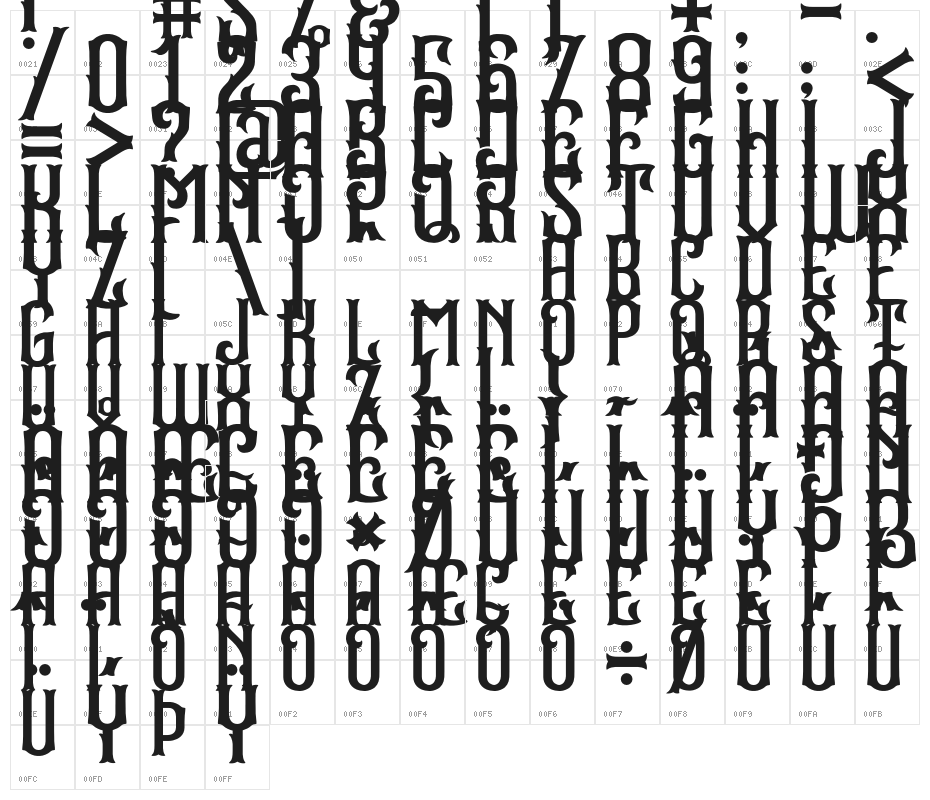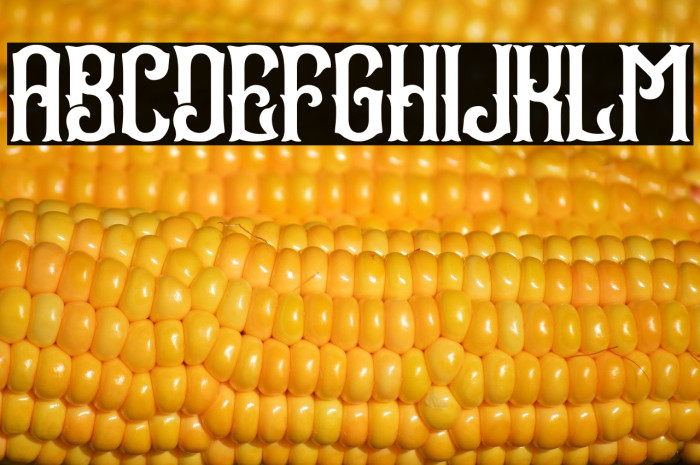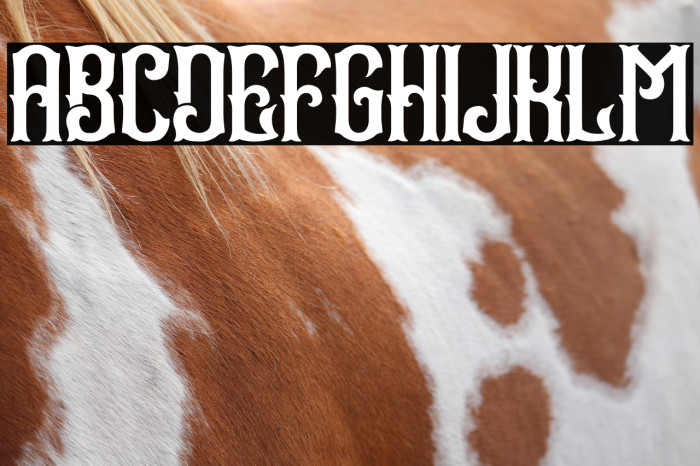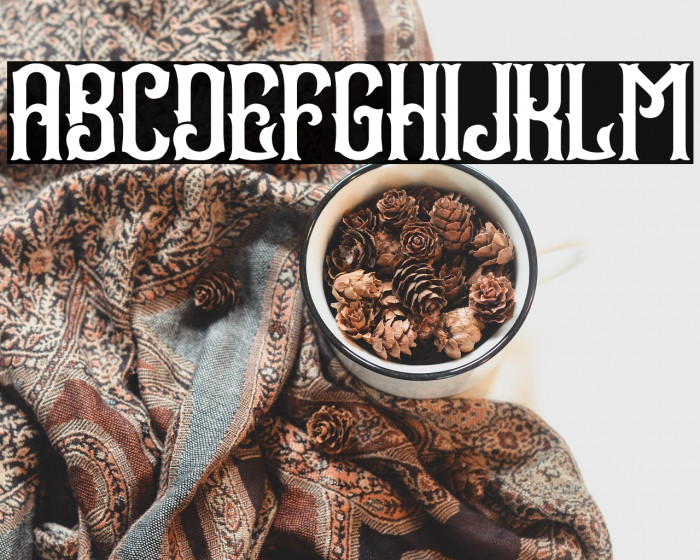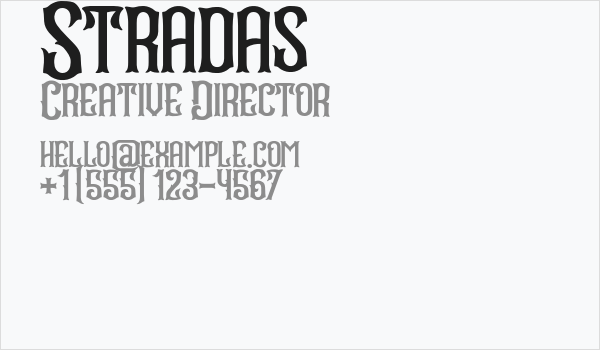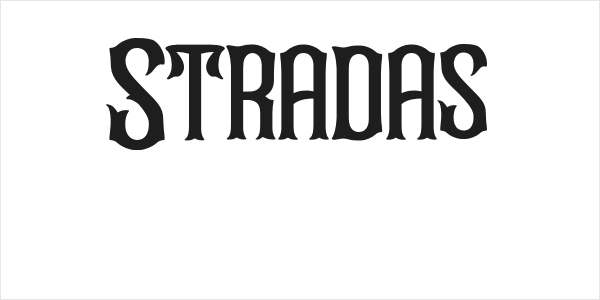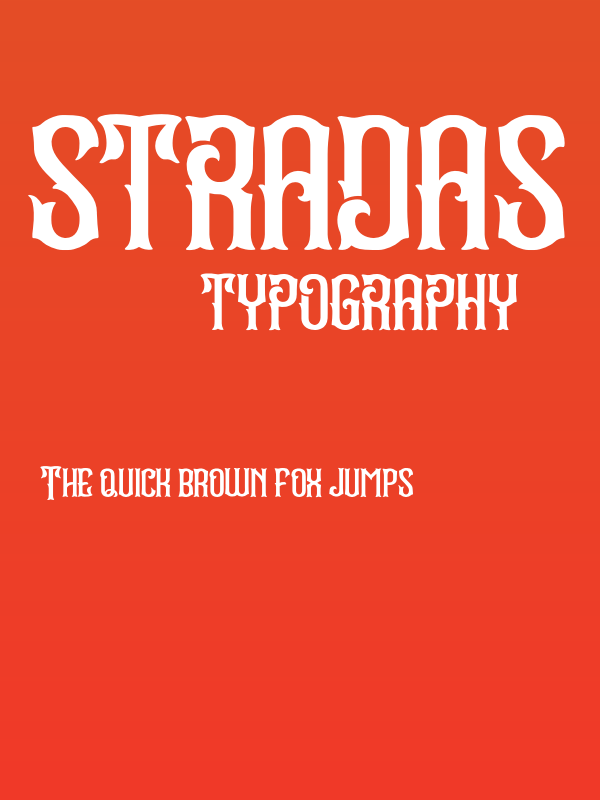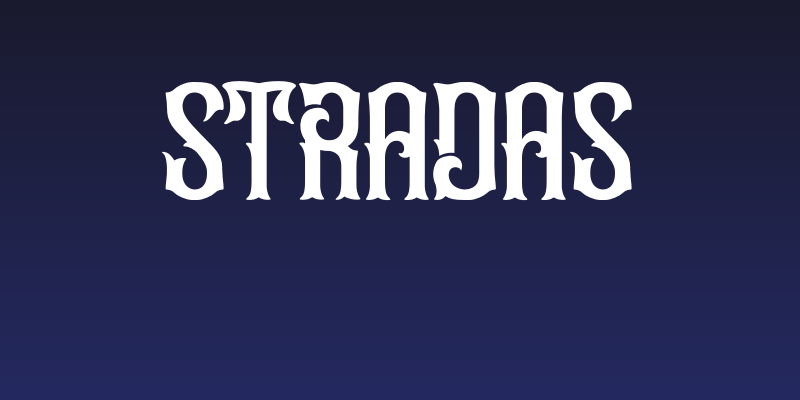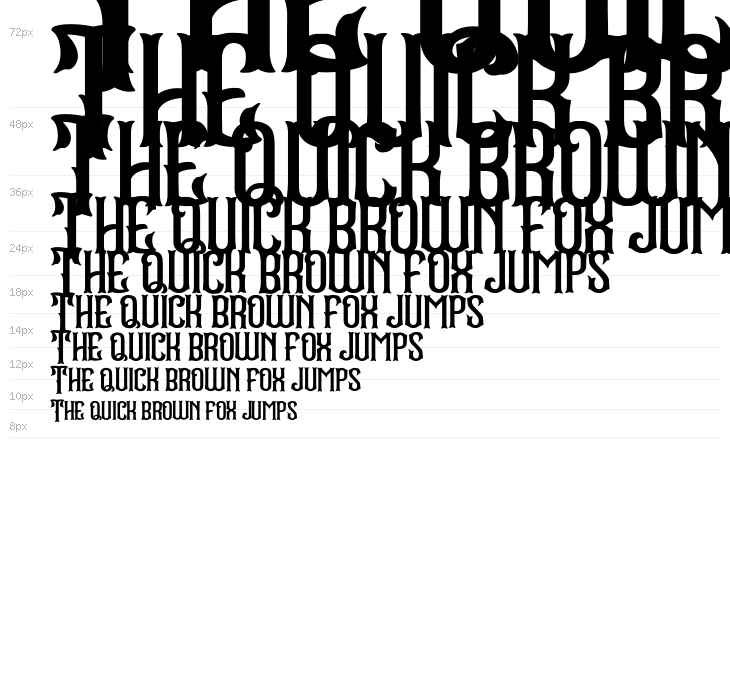
Stradas Font
✎ Gothic
| الفئات | Gothic |
| العرض | Condensed |
| مشاريع مقترحة | Ideal for projects that require a dramatic and eye-catching typeface, such as posters, album covers, branding for edgy or alternative products, and event invitations. |